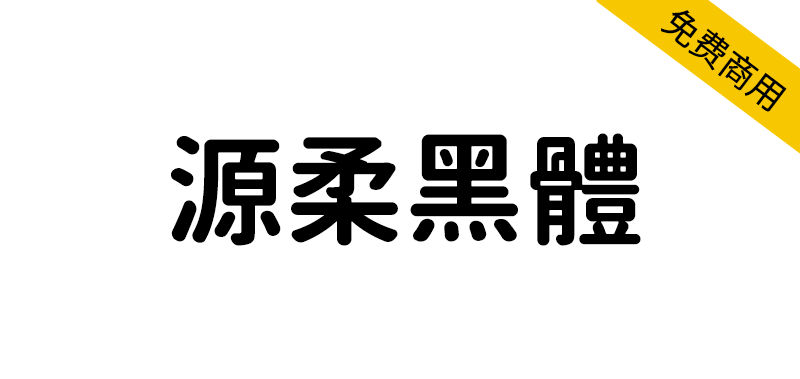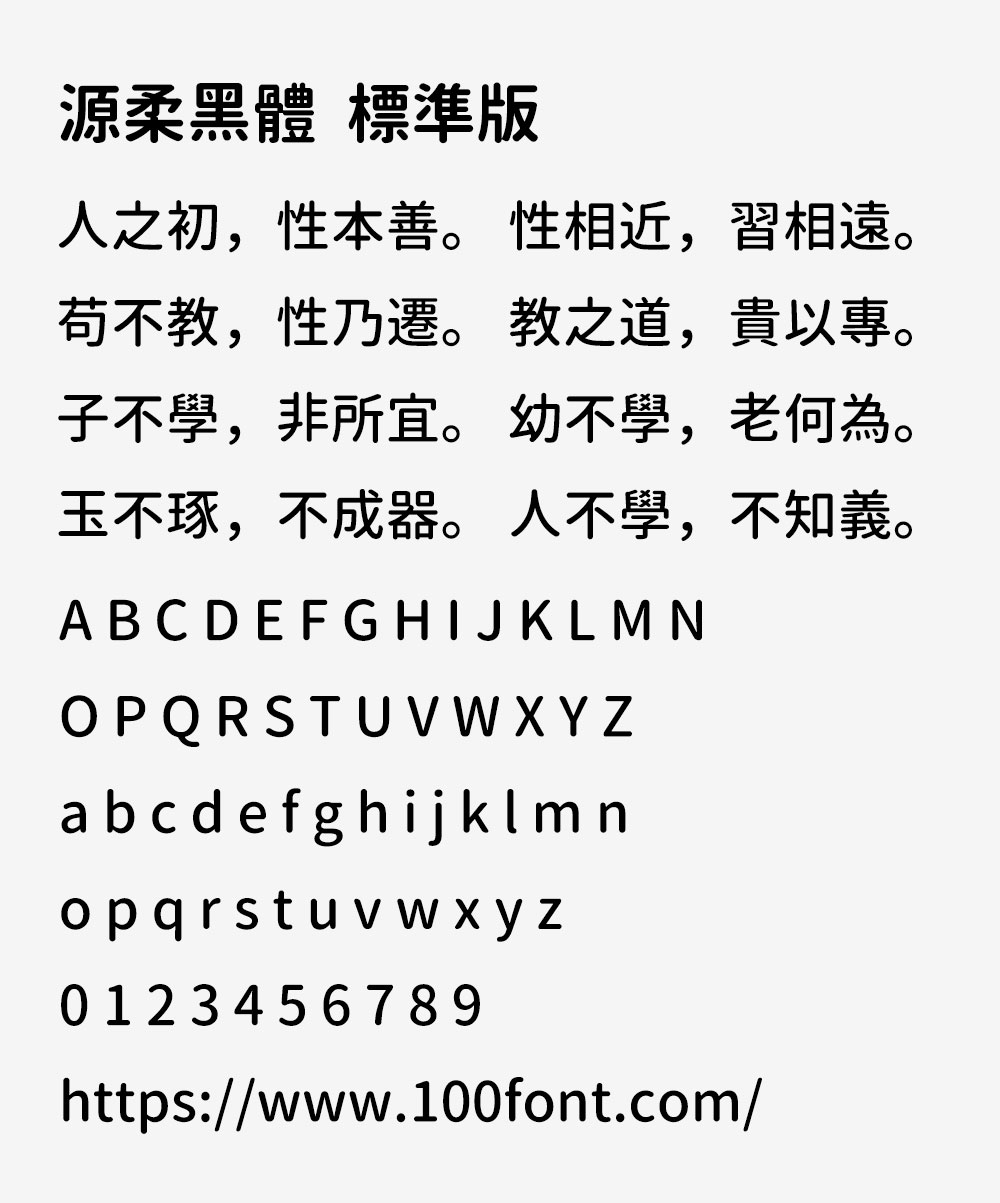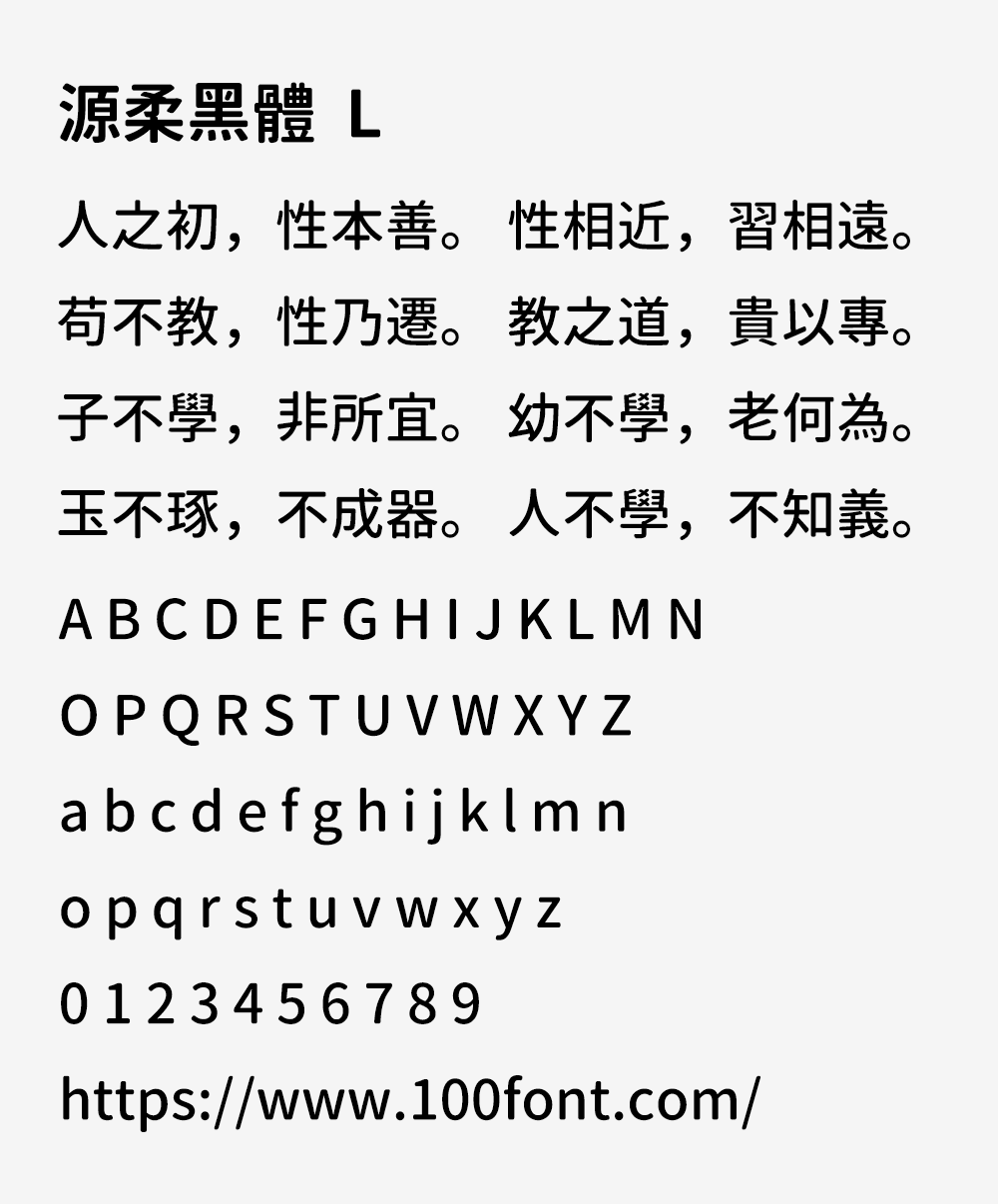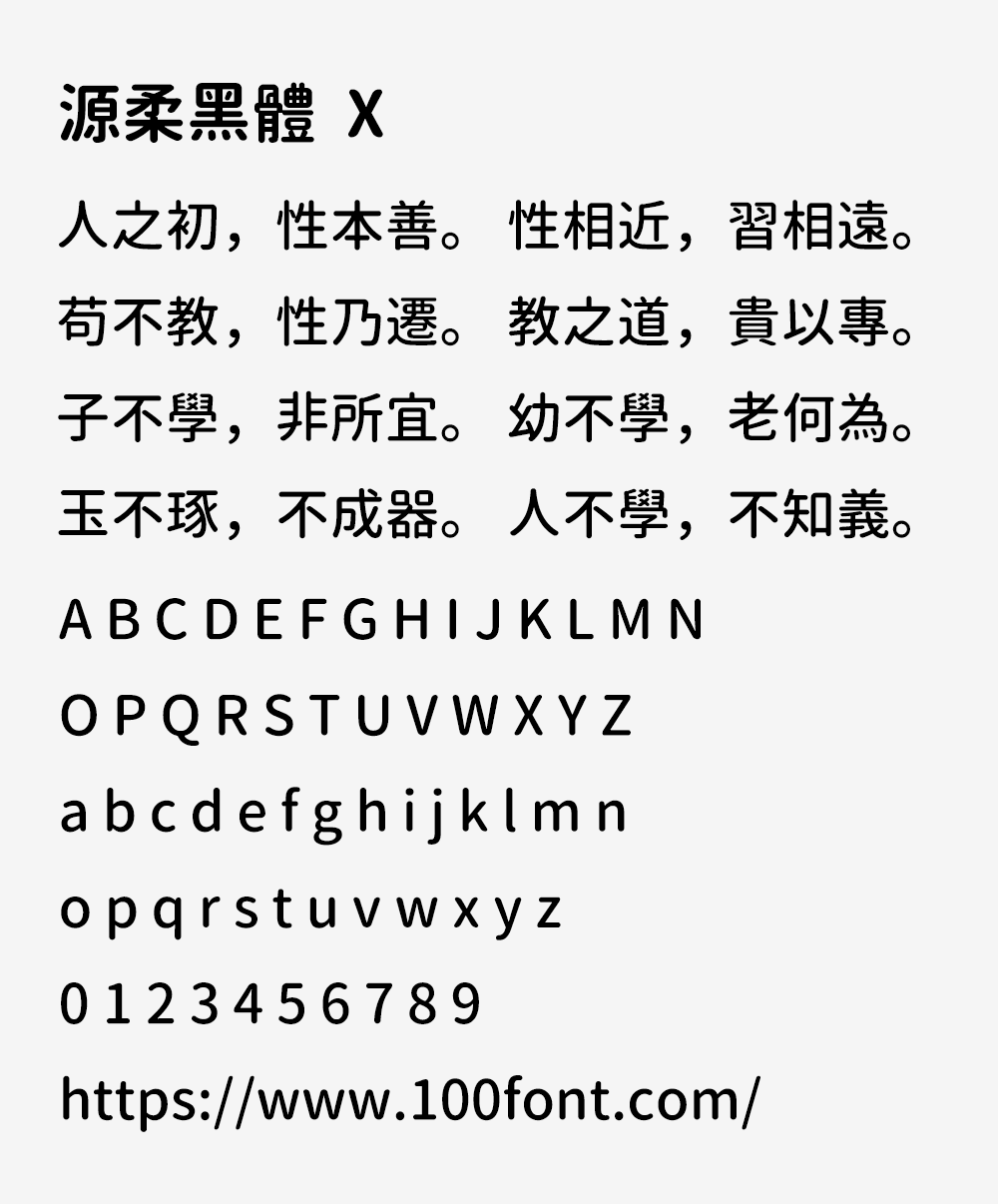
源柔黑体(源柔ゴシック)和源真黑体(源真ゴシック)是日本 自家製フォント工房基于开源字体“思源黑体”修改制作衍生而来,支持繁体中文以及日文。两款字体都是开源免费的,应用场景非常广泛。
源柔黑体一共发布了 3 个版本,分辨是标准版、L、X。它们的区别在于圆角的圆润程度不同,L 圆角最小 (最尖),X 圆角最大 (最圆),而标准版则是介于两者之间。每个版本都有 7 种字重,3种字形样式 (包括等宽字体)。